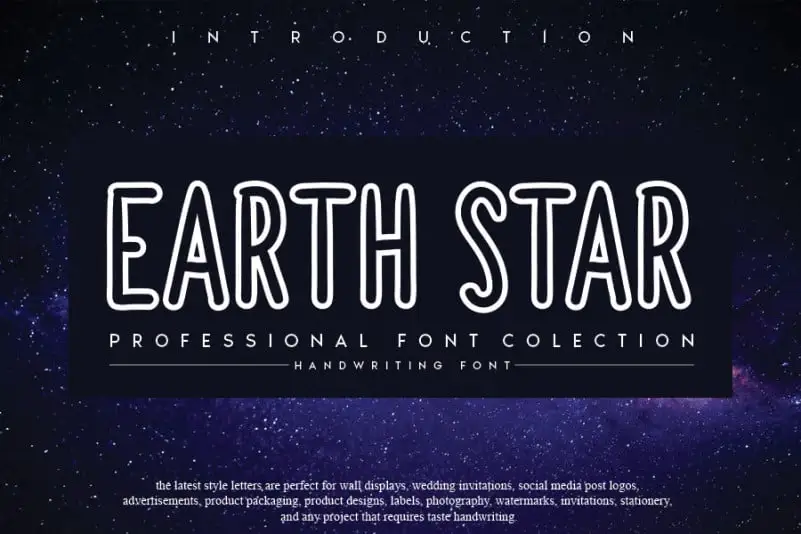
EARTHSTAR Display Font – Download Grátis
EARTHSTAR Display Font é uma elegante fónt criada com um toque mágico que mistura o charme da escrita a mão com o encanto do estilo calligrafia autêntica. Esta fónt tem sido cuidadosamente desenvolvida para trazer beleza e refinamento a uma ampla gama de projetos de design, desde marca, cabeçalhos, designs de casamentos até convites, assinaturas, logotipos, etiquetas, e muito mais! Este font não apenas eleva seus trabalhos ao nível máximo, mas também transforma o simples texto em um elemento poderoso e único que destaca-se na comunicação visual. EARTHSTAR Display Font é uma escolha inteligente para quem deseja dar um toque especial a suas criações, seja no escritório de design ou na sua próxima arte pessoal.